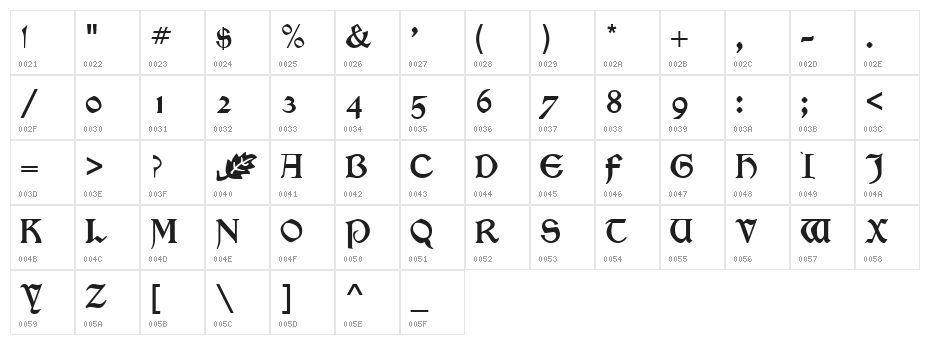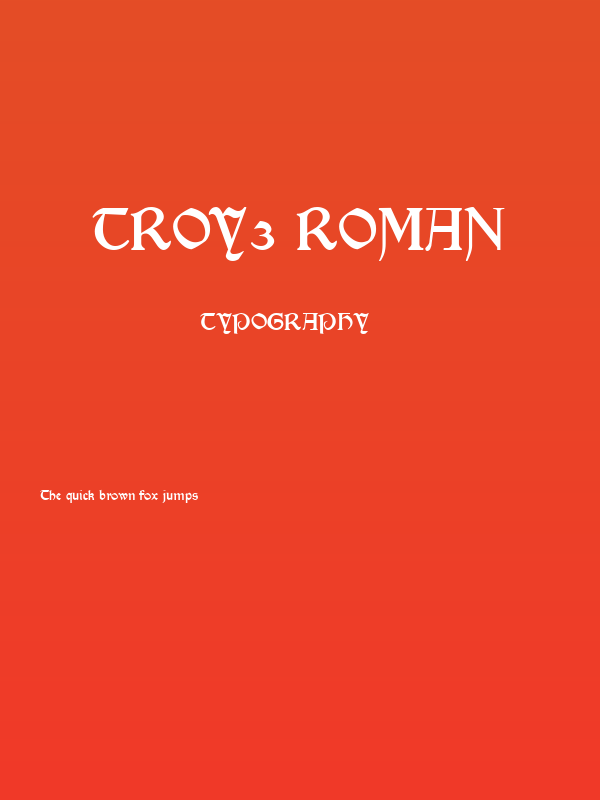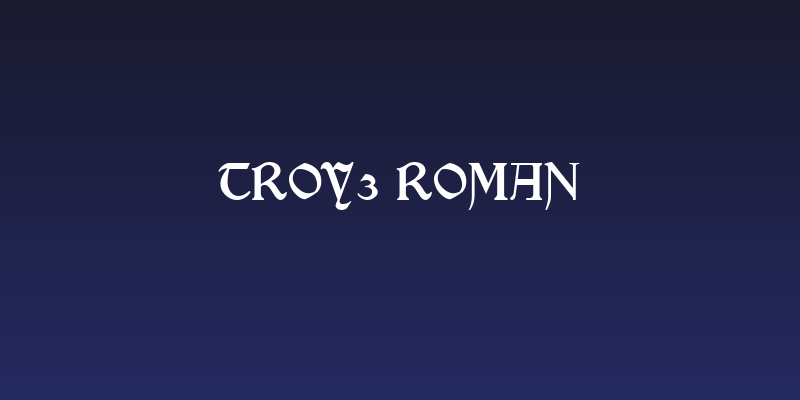
Troy3 Roman Font
✎ Gothic
| Caso d'uso | Logos, Headlines, Certificates |
| Progetti proposti | Suitable for historical documents, certificates, branding for luxury goods, or any project needing a traditional and elegant touch. |